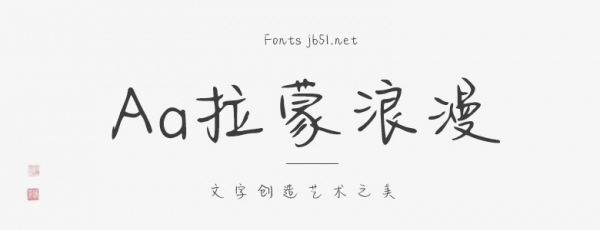
Aa拉蒙浪漫是一款很優(yōu)秀好用的浪漫藝術(shù)字體,該字體的筆畫結(jié)構(gòu)看上去非常的美觀,書寫效果非常的圓潤,給人一種浪漫的藝術(shù)氣息,另外字體線條粗細(xì)適中,筆畫隨性,結(jié)構(gòu)很隨性,整體效果十分的獨特。具有很好的視覺感,適合于文化類的宣傳設(shè)計、商業(yè)類品牌的廣告和產(chǎn)品包裝設(shè)計以及個性化文字排版等較多場景。